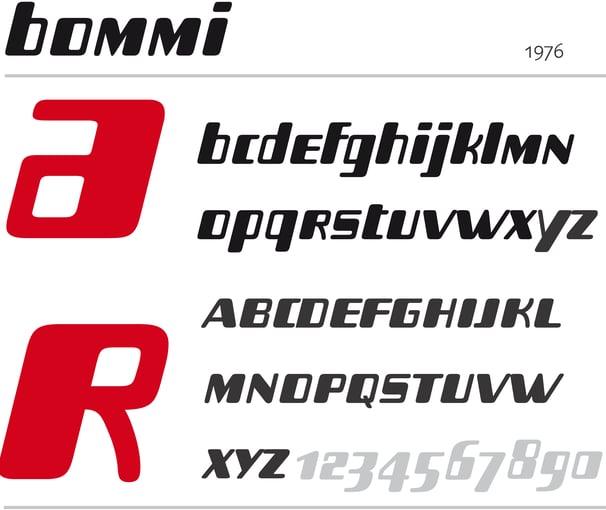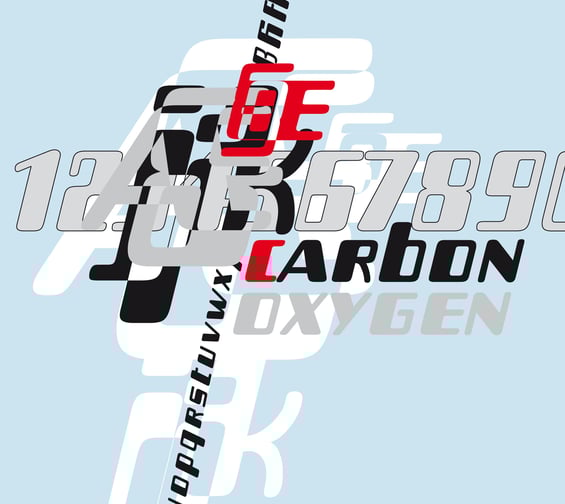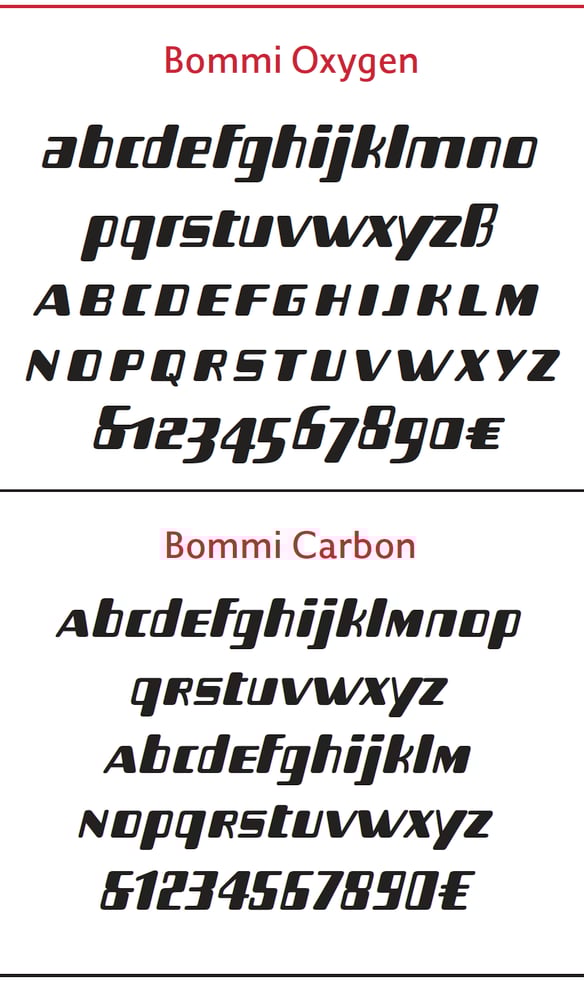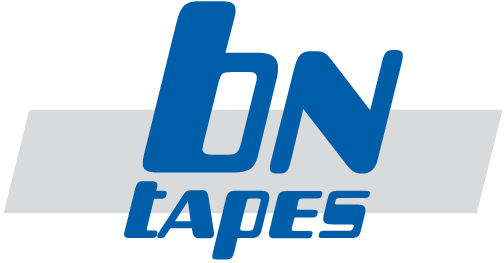
Bommi
Die ersten Buchstaben der bommi entstanden 1976 bei einem Auftrag für einen Firmenschriftzug. Aus Frust über den geizigen Kunden machte ich einen kompletten Zeichensatz mit Namen Knicker daraus. So entstanden mit der »Image’n’transfer«- Methode von 3M eigene Anreibe-Bögen. Die bommi hat sich mehrfach bei der Gestaltung von Schriftzügen bewährt, zuletzt 1999 für die Sulzbacher Firma »bntapes«. Für die Frontplatte eines elektronischen Mess- und Regelgeräts entwarf ich den Schriftzug oxygen carbon controller. Hiervon bekamen die beiden Schnitte der bommi ihre Namen. Die Bommi wurde im FontForum von URW Type Foundry veröffentlicht.